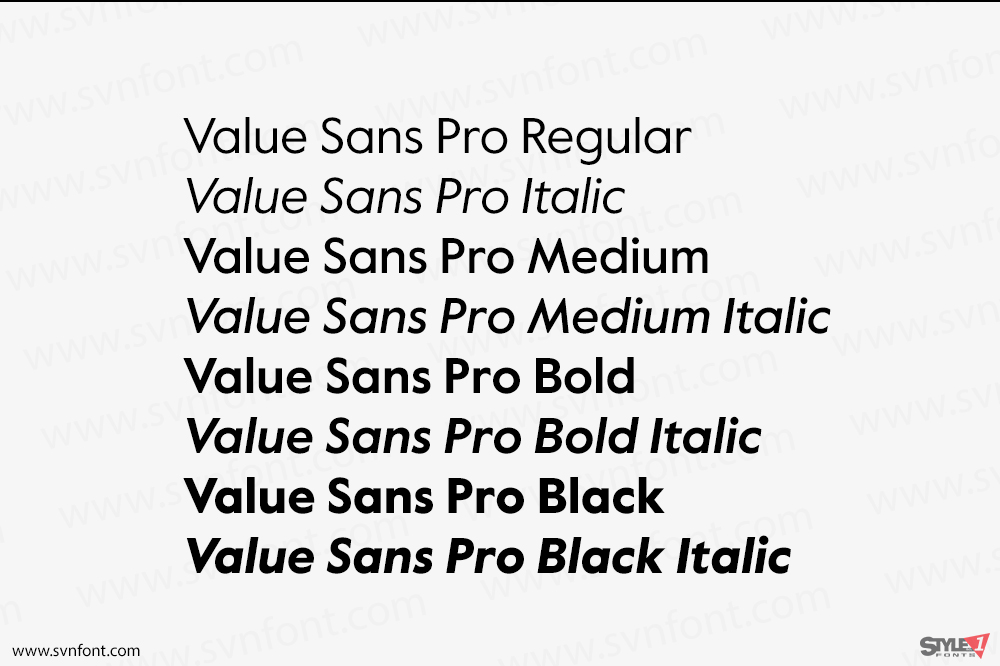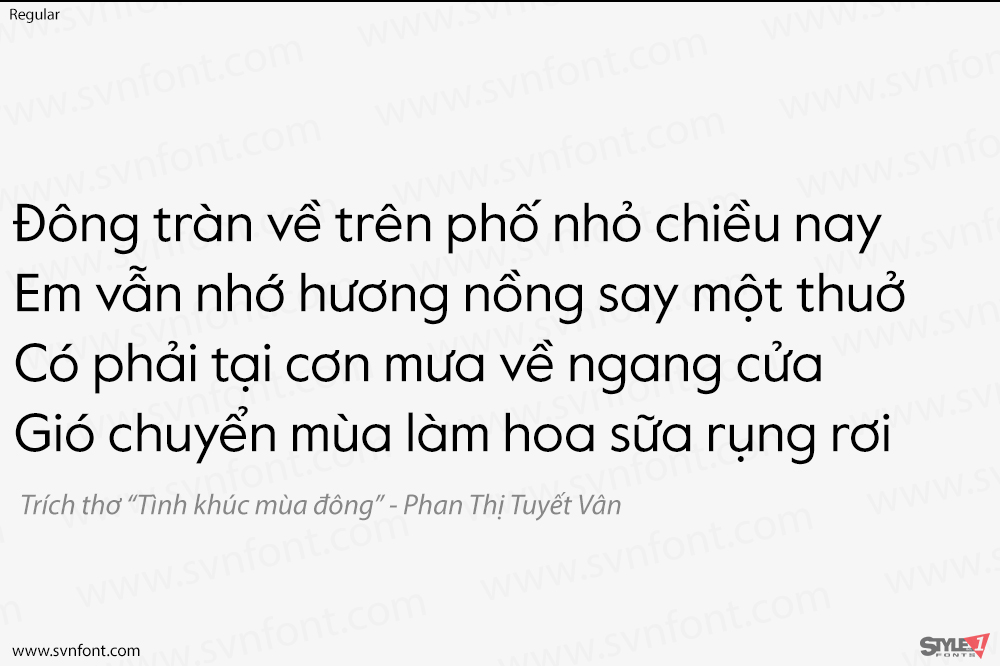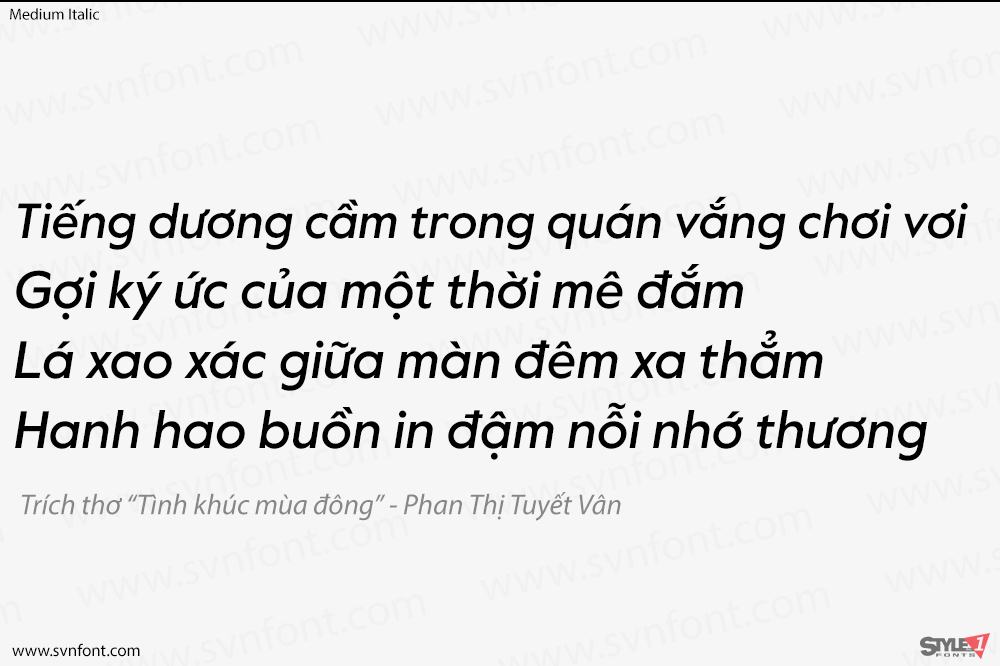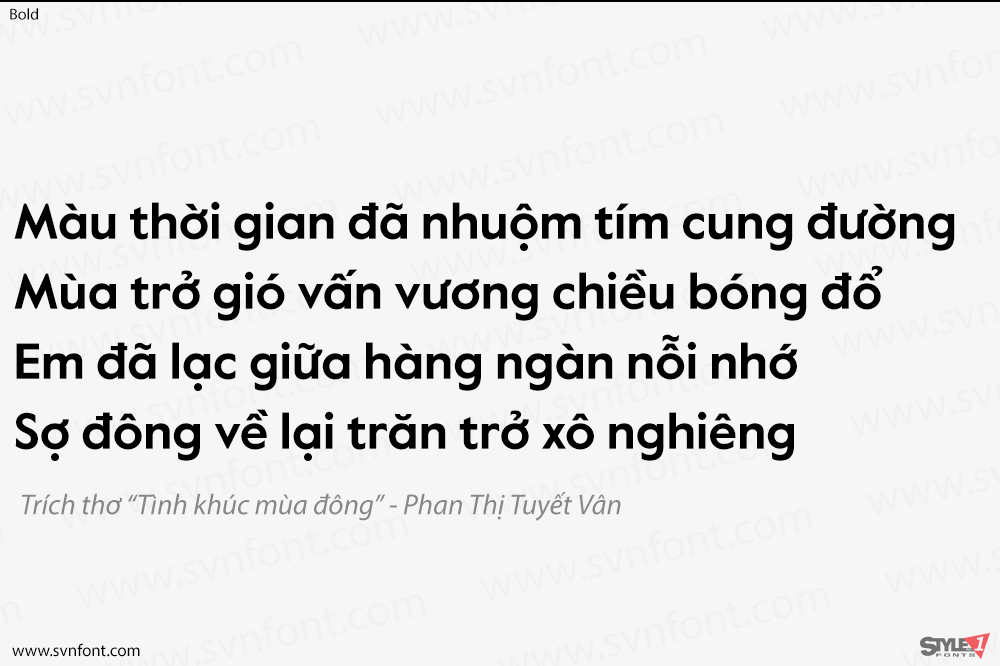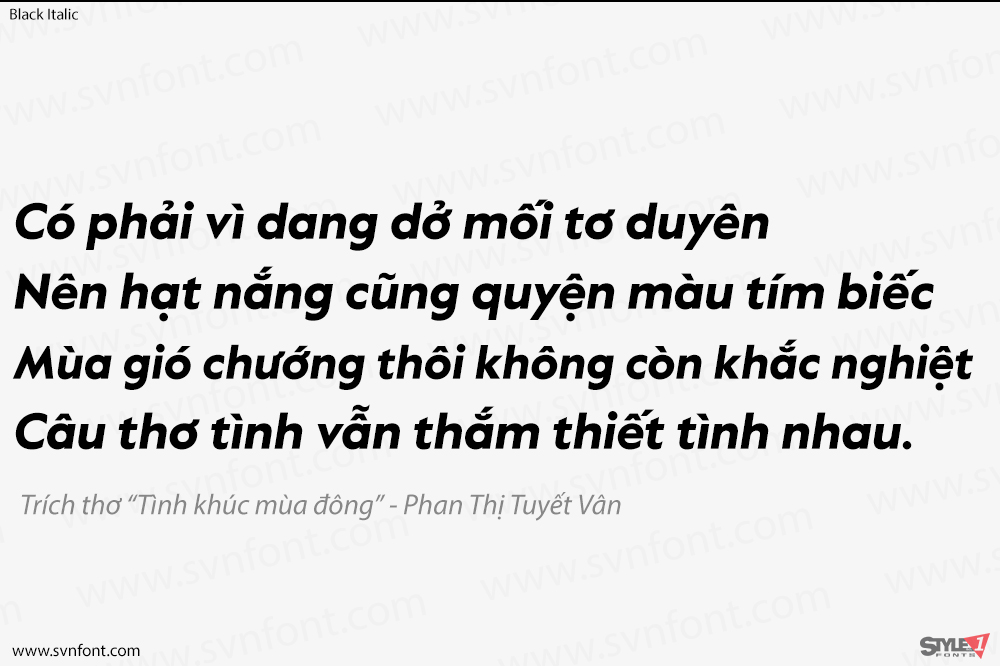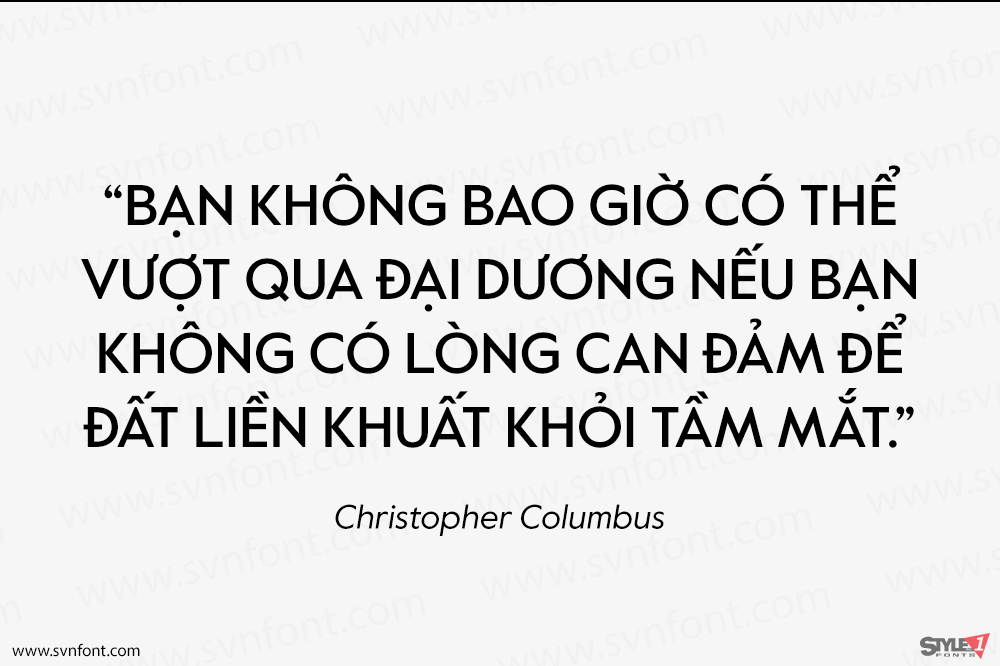
Value là một họ phông chữ đương đại gồm hai kiểu chữ: Value Sans và Value Serif. Cả hai phiên bản này đều được vẽ dựa trên các cuộc trò chuyện xoay quanh các khái niệm về trao đổi văn hóa và tài chính: Value Sans mượn phong cách và đặc điểm từ các tiền lệ như Elegant Grotesk (Đức) và Granby (Anh); Value Serif tôn vinh những kiểu chữ đi trước như Plantin Infant (Pháp + Mỹ) và Italian Old Style (Mỹ).
Nhà thiết kế: Benjamin Critton, Colophon Foundry
Nhà phát hành: Colophon Foundry